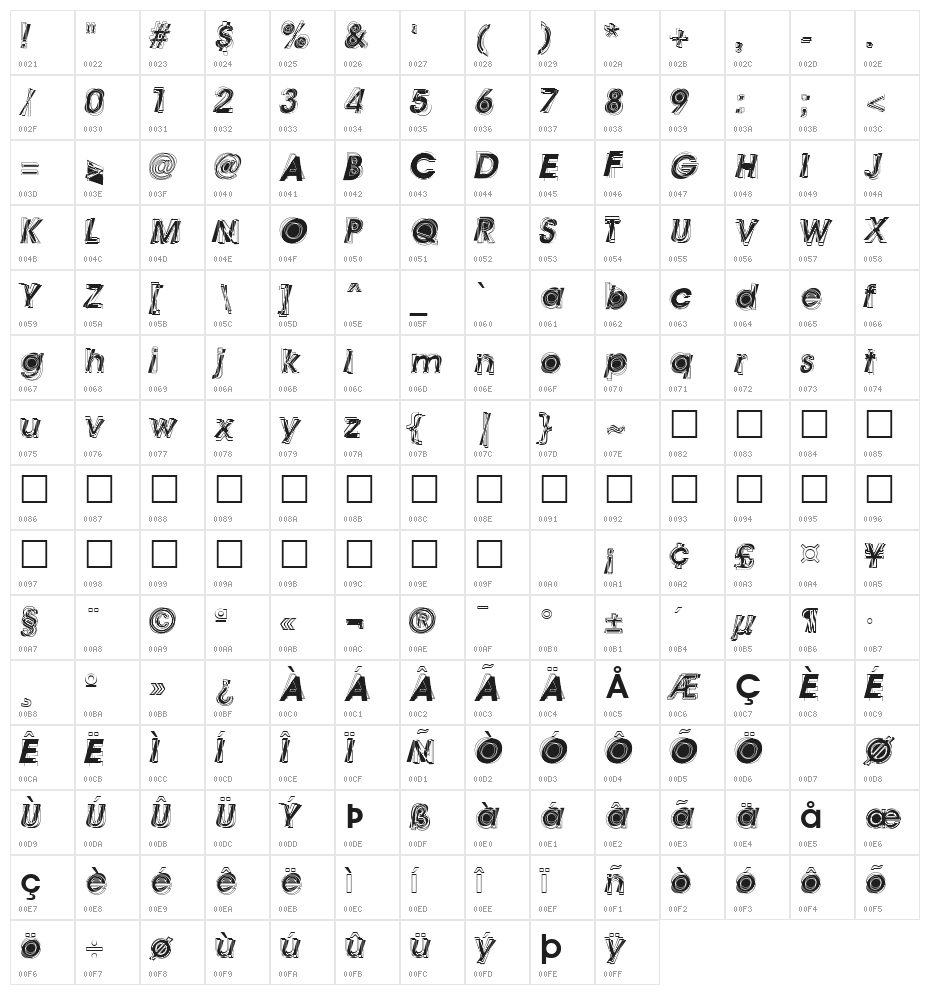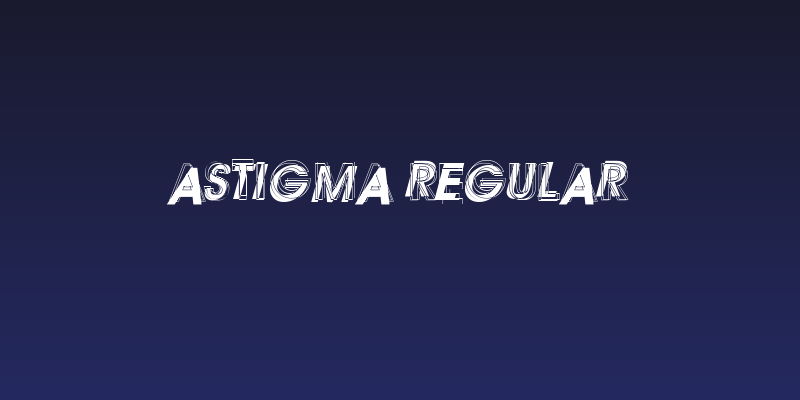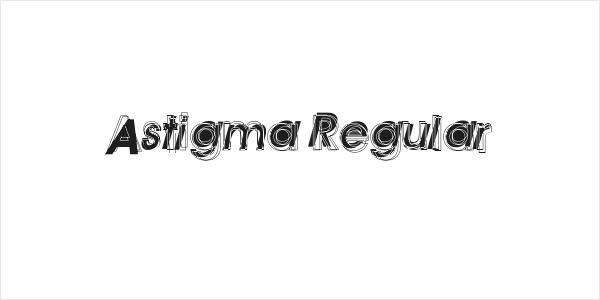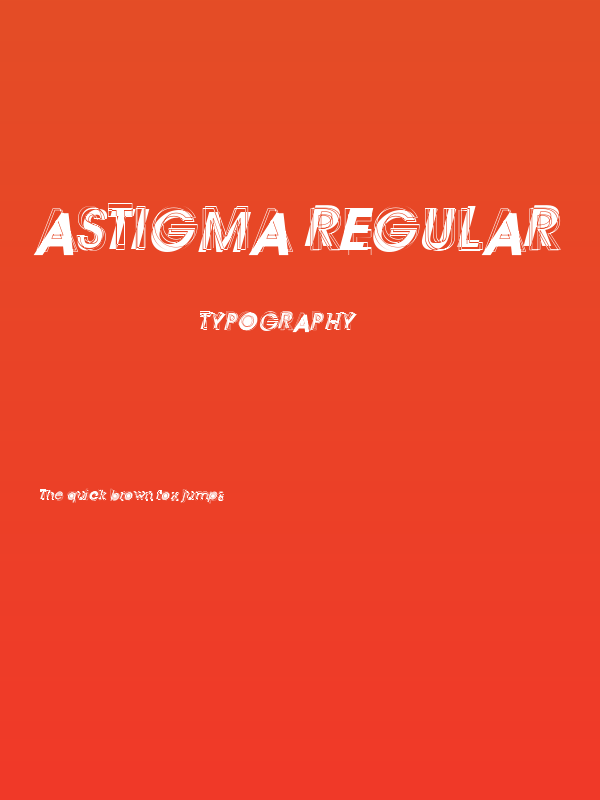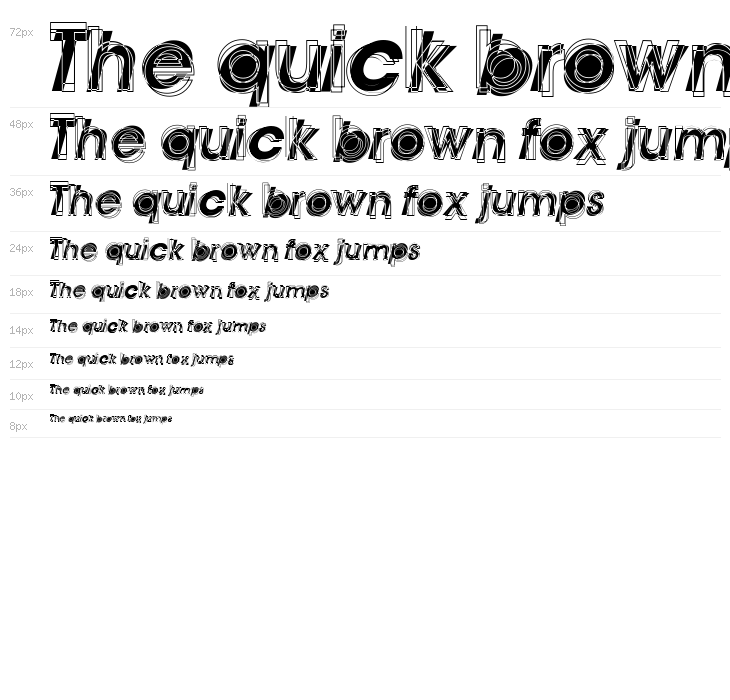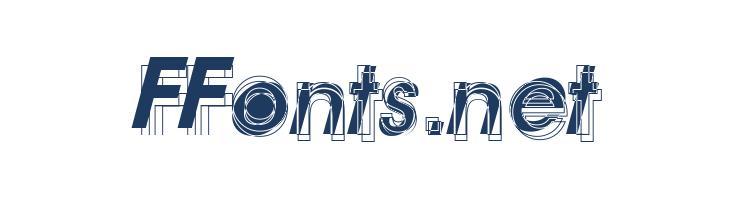
Astigma Regular Font
| Proyectos propuestos | Ideal for posters, album covers, branding, and any project that seeks to capture attention with a modern and artistic touch. |